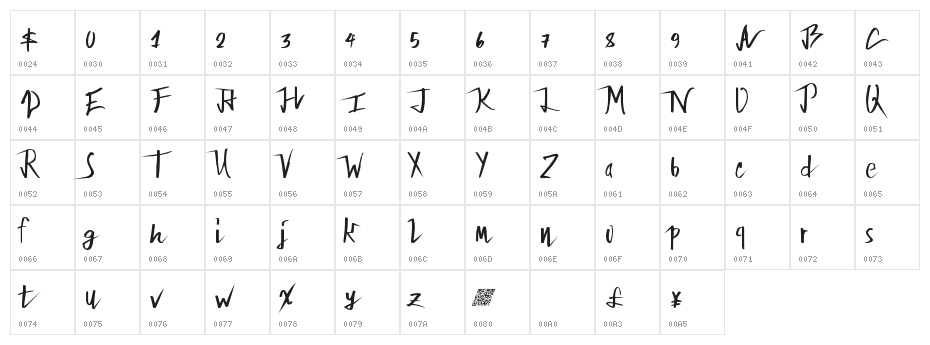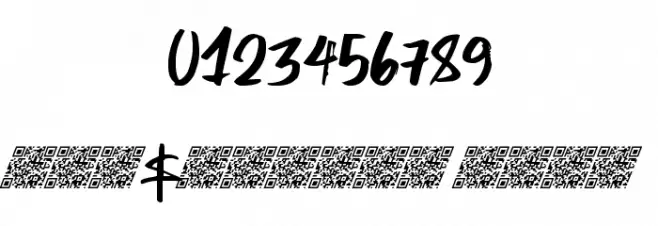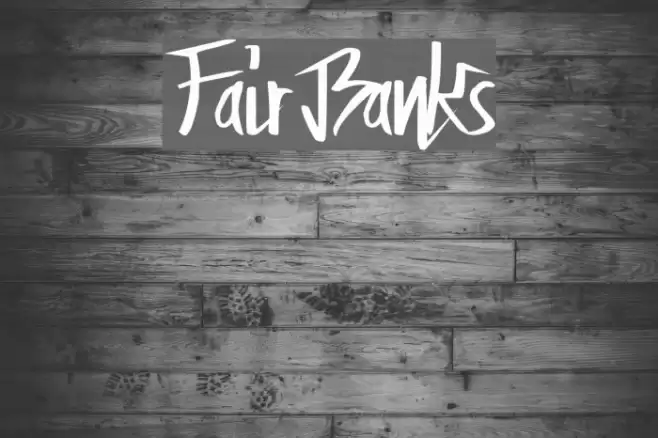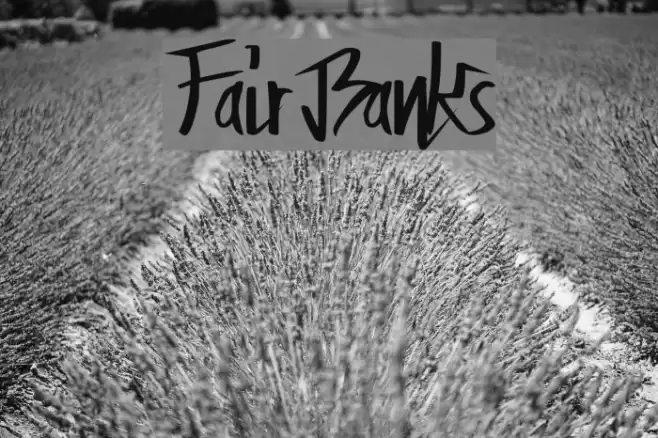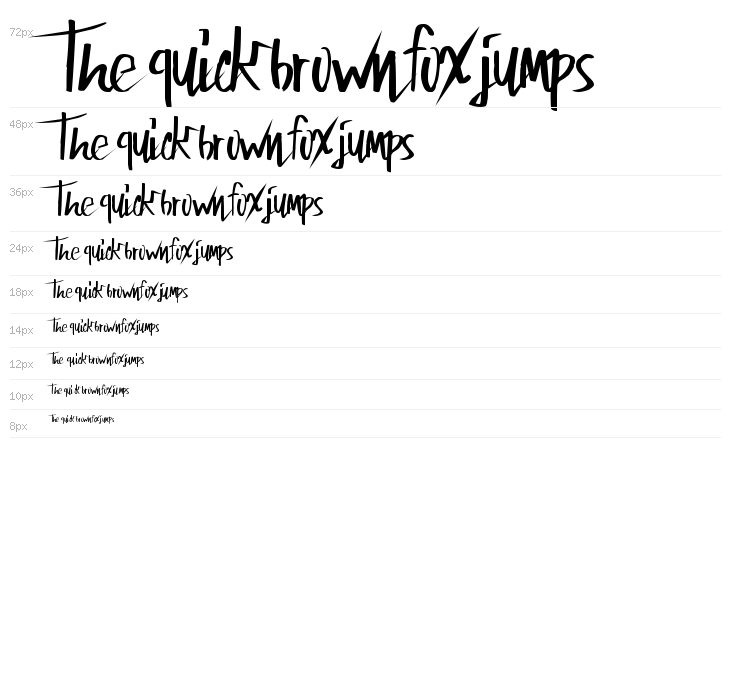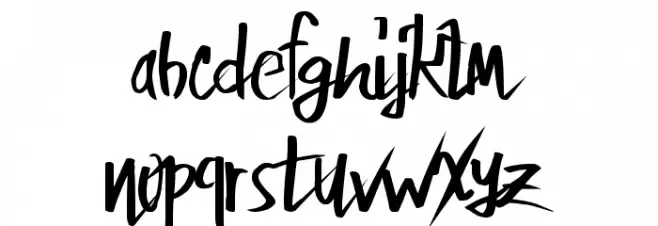
FairBanks Font
✎ Graffiti
| Categorie | Graffiti |
| Caso d'uso | Logos, Posters, Headlines |
| Progetti proposti | Ideal for branding, posters, album covers, and any design project that requires a bold, artistic flair. |